Typografi er mere end bare bogstaver på en side; det er en afgørende del af visuel identitet og branding. Tænk på dine yndlingsbrands – chancerne er, at de har en genkendelig skrifttype, der øjeblikkeligt fremkalder en bestemt følelse eller association. Fra logoer til marketingmaterialer spiller valget af skrifttype en enorm rolle i, hvordan et brand opfattes. To fremragende eksempler på brands, der forstår skrifttypens magt, er Hello Kitty og Pusheen, som begge bruger unik typografi til at forstærke deres søde og elskelige personligheder. Men hvordan finder man ud af, hvilken skrifttype der bruges, og endnu vigtigere, hvordan kan du selv bruge særlige skrifttyper i dine egne projekter, hvad enten det er til fotografering (vandmærker, grafik), design eller noget helt tredje?
Denne artikel vil udforske skrifttyperne bag disse populære figurer og give dig en praktisk guide til at installere og administrere skrifttyper på din computer, så du kan løfte dine egne kreative bestræbelser.
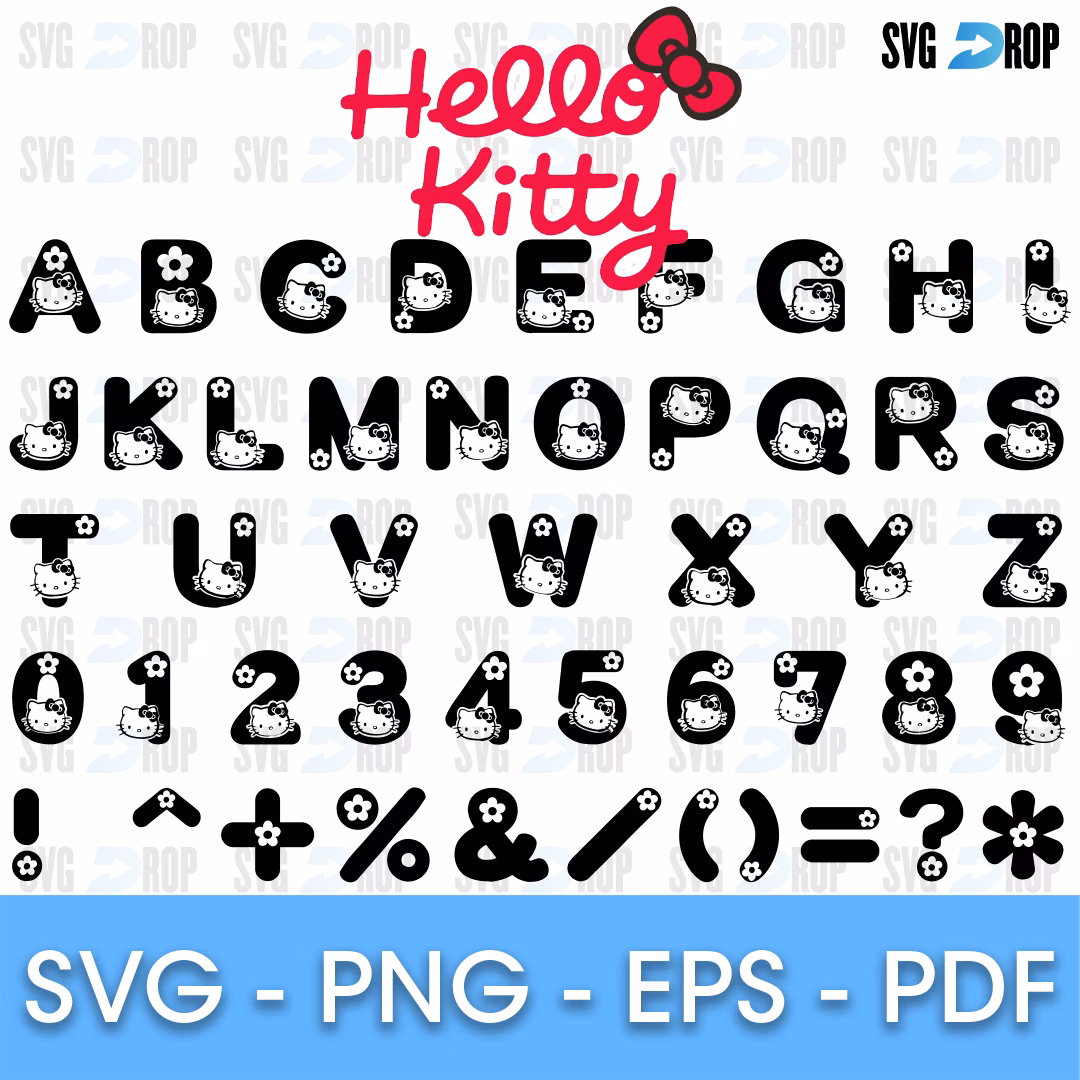
Hvad er Hello Kitty Skrifttypen?
Når folk spørger om "Hello Kitty skrifttypen", tænker de ofte på den skrifttype, der bruges i selve Hello Kitty-logoet eller brandets markedsføringsmaterialer. Sandheden er, at der ikke er én enkelt, navngiven skrifttype, der universelt identificeres som "Hello Kitty skrifttypen". I stedet bruger Sanrio, virksomheden bag Hello Kitty, forskellige skrifttyper i deres branding, især i forbindelse med logoets ordmærke (selve navnet "Hello Kitty").
Siden Hello Kittys visuelle identitet blev skabt i 1974, har logoet i sig selv forblevet stort set uændret – det ikoniske billede af katten med den røde sløjfe. Men det tilhørende ordmærke, altså teksten "Hello Kitty", har varieret gennem årene. Man har set versioner med både script/kursiv skrifttype og specialdesignede sans-serif skrifttyper. Disse variationer er ofte tilpasset det specifikke produkt eller den kampagne, de bruges til. Det vigtigste er, at uanset den præcise skrifttype, der vælges til ordmærket, komplementerer den Hello Kittys overordnede æstetik: sød, venlig og legende. Typografien er med til at understrege brandets personlighed og genkendelighed på tværs af et utal af produkter og platforme verden over. Denne fleksibilitet i skrifttypevalget for ordmærket viser, hvordan forskellige typografiske stilarter kan bruges til at formidle nuancer inden for samme brandidentitet.
Pusheens Unikke Skrifttype
I modsætning til Hello Kitty, hvor ordmærket varierer, er Pusheen kendt for at have en mere specifik, specialdesignet skrifttype skabt eksklusivt til brandet. Denne skrifttype er en sød, kursiv skrifttype, der blev udviklet af Chank Co. Man har blandt andet set den brugt på skiltning og menuer i "Pusheen Snack Parlor" pop-up-butikken i Brighton, England. En specialdesignet skrifttype som denne er et kraftfuldt redskab for et brand. Den sikrer fuldstændig unikhed og er perfekt skræddersyet til at afspejle Pusheens dovne, madelskende og utroligt nuttede personlighed. Når du ser denne skrifttype, tænker du straks på Pusheen, hvilket er præcis målet med effektiv branding. Det er et glimrende eksempel på, hvordan et brand investerer i sin visuelle identitet ned til mindste detalje – bogstavernes form.
Hvorfor er Skrifttyper Vigtige for Branding og Design?
Valget af skrifttype er fundamentalt for et brands succes. Typografi skaber en stemning og kommunikerer brandets værdier og personlighed, selv før nogen har læst et eneste ord. En fed, robust skrifttype kan signalere styrke og pålidelighed, mens en let, kursiv skrifttype kan formidle elegance og kreativitet. For brands som Hello Kitty og Pusheen er det afgørende at vælge skrifttyper, der understreger deres "kawaii" (japansk for nuttet) appel. En velvalgt skrifttype forbedrer læsbarheden, skaber et professionelt udseende og, vigtigst af alt, bidrager til en stærk, genkendelig brandidentitet. I en verden, hvor visuelt indhold dominerer, er typografi et af de mest tilgængelige og effektive værktøjer til at fange opmærksomhed og skabe et varigt indtryk. Dette gælder ikke kun for store virksomheder, men også for enkeltpersoner og små virksomheder, der ønsker at opbygge et personligt brand, for eksempel fotografer, der designer deres logo, visitkort eller vandmærker til billeder.
- Træk og slip skrifttypefilen (eller flere filer) direkte ind i "Font Book"-vinduet.
- "Font Book" vil nu installere skrifttypen. Du vil se den dukke op i listen sammen med dine andre installerede skrifttyper.
- Du kan bruge "Font Book" til at organisere dine skrifttyper, få vist eksempler og endda aktivere eller deaktivere skrifttyper for at holde din liste ryddelig.
Installation af Skrifttyper på PC (Windows)
På en PC er processen endnu enklere.
- Find den skrifttypefil (.otf eller .ttf), du vil installere.
- Højreklik på skrifttypefilen.